磅数
(Read More)在字体设计中,磅数是描述字体(印刷或数字媒体)大小的测量单位。
几个世纪以来,世界各地创造并使用了多种单位,从 “Didot” 到 “Cicéro”,再到 “Pica” 和许多其他单位。如今,国际标准单位名称是(字体排印)磅。字体大小被称为磅数大小,用 pts 表示。
版权页
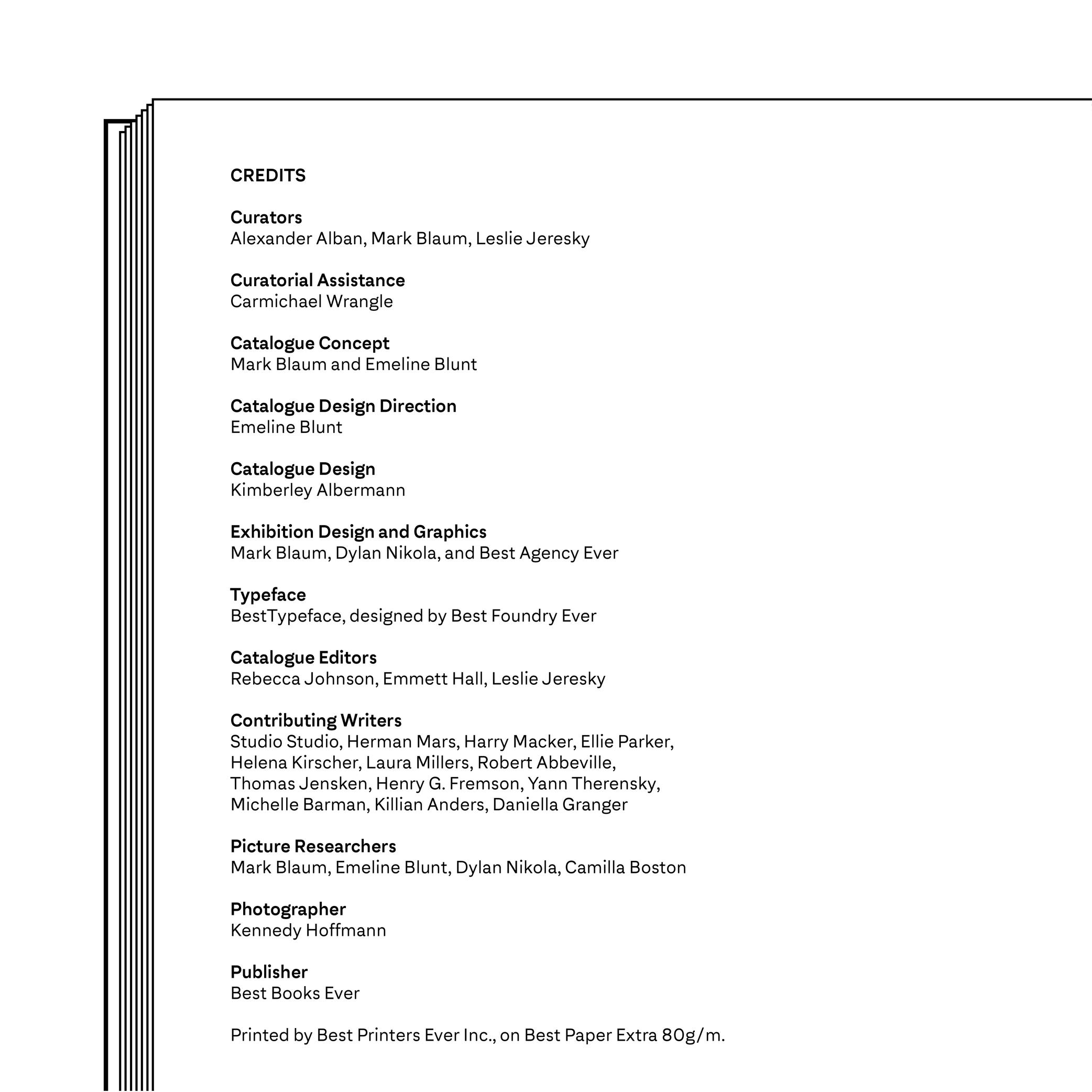
(Read More)版权页(或出版说明)是有关作品或项目制作的提示性信息列表。其范围包括参与人员的姓名和角色、所用字体、纸张的品牌和种类、生产商和生产地点,以及网站的域名等等。
贝齐耶曲线
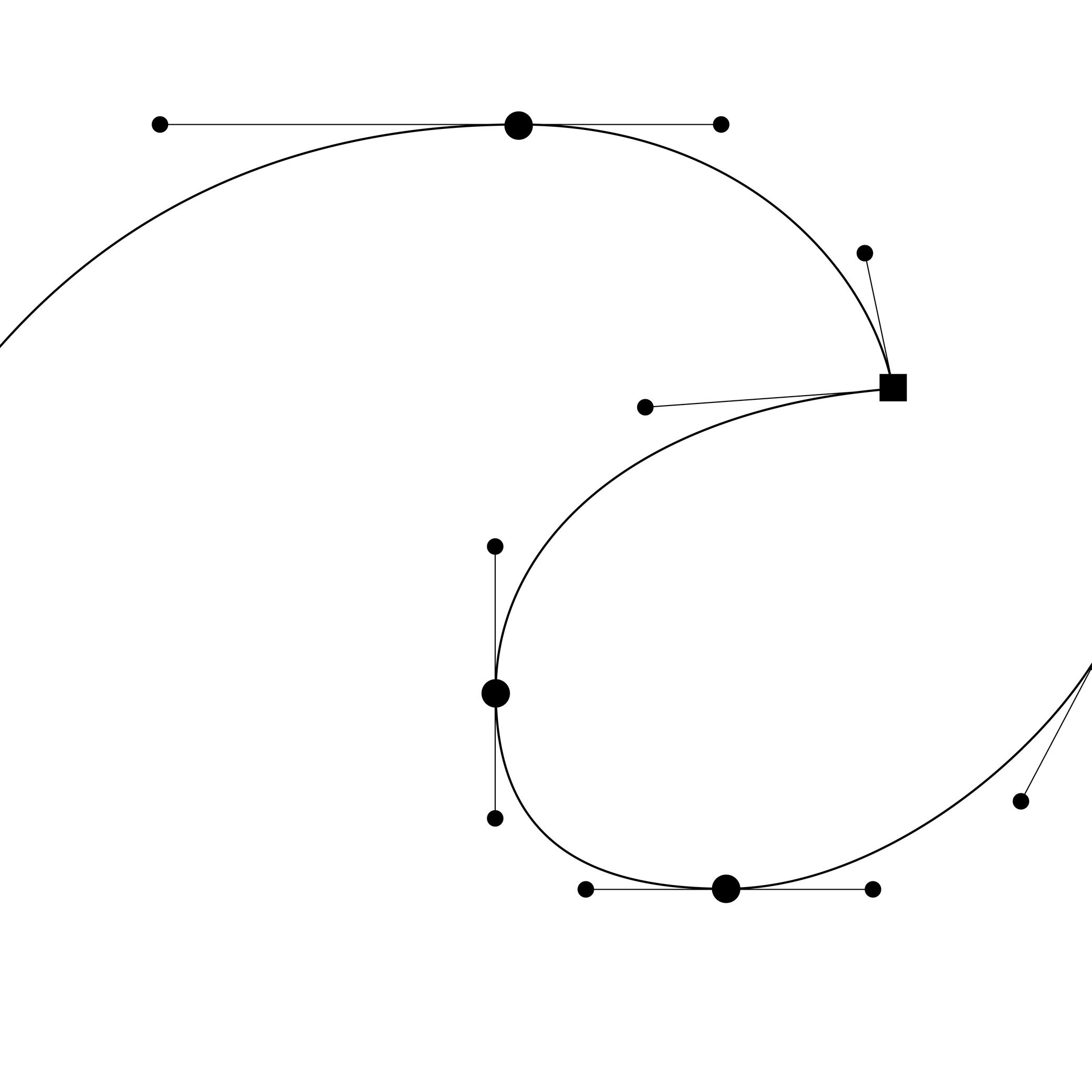
(Read More)在字体设计中,贝齐耶曲线是在数字化软件中放置节点和手柄来绘制的矢量轮廓。这种技术允许我们将数字形状记录并栅格化地再现出来,并保持曲线质量不发生太大变化。
历史
贝齐耶曲线是由法国数学和物理学家保尔·德·卡斯特奥(Paul de Casteljau)在1959年开发的。当时他正在为汽车品牌雪铁龙工作,他发明了一个数学方程式以改进汽车外壳的设计过程。法国工程师皮埃尔·贝齐耶(Pierre Bézier)在为雷诺汽车工作时使用了同样的技术,利用数字工具创造出了造型。直到 1985 年,雪铁龙解除了工业保密条款,德·卡斯特奥才得以谈论自己的工作,皮埃尔·贝齐耶也得以公开提及自己的工作。
1982年,贝齐耶曲线被美国计算机科学家约翰·沃诺克(John Warnock)用于为他与查尔斯·格斯克(Charles Geschke)共同创立的公司开发描述和定位数字造型和轮廓的技术:Adobe系统。
更多
贝齐耶曲线有两种类型:三次曲线和二次曲线。
一个三次贝齐耶曲线需要四个点的定位(两个点和两个手柄),在两两点之间形成了三段线条。Postscript字体格式使用三次曲线。
二次曲线由三个点(两个点和一个控制点)来创建一条曲线,中途有两个部分被切断,以确定曲线在哪里转到另一个点。TrueType字体格式使用二次曲线。
备选字符形
(Read More)由于多种原因,字符形可以有很多的变体。 最常见的有以下:
- 特定的语境(例如针对大写字母,原本为小写适配的标点符号可以替换成与大写字母对齐的字符形);
- 字符形的风格变体(例如花体字的备选);
- 本地化语言的偏好(本地化变体)。
在数字文件中,它们的名称都有与 Opentype 特性代码对应的标签(parenleft.case、A.swsh、Ldot.locl 等等),因此它们能轻松地在支持这些特性的应用程序中被处理。
边距
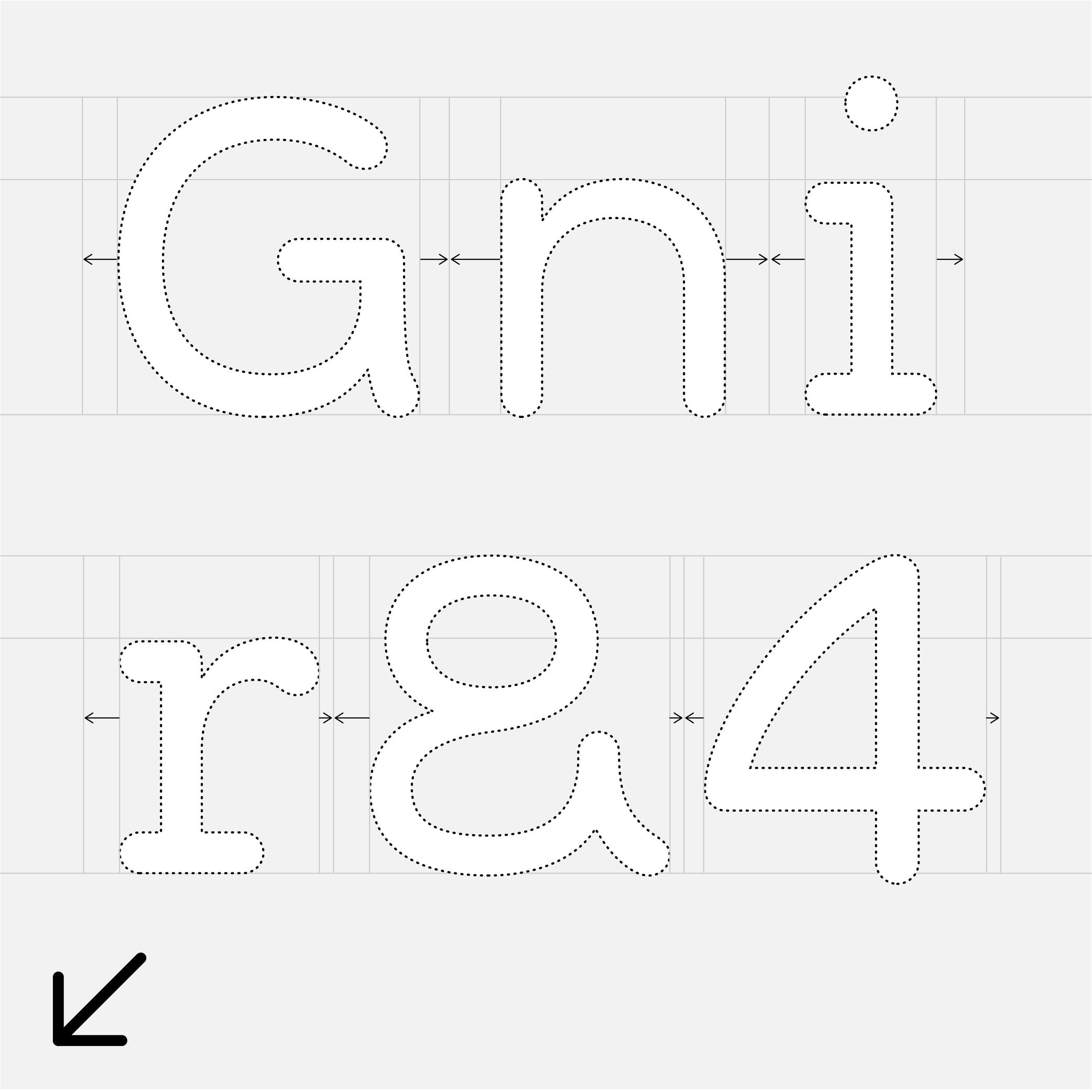
(Read More)边距是指字形的侧面与其边界框之间的距离。在水平书写的字体中,总是存在左边距 (LSB) 和右边距 (RSB)。管理边距值就是管理 “字体的字间距”。
变音符
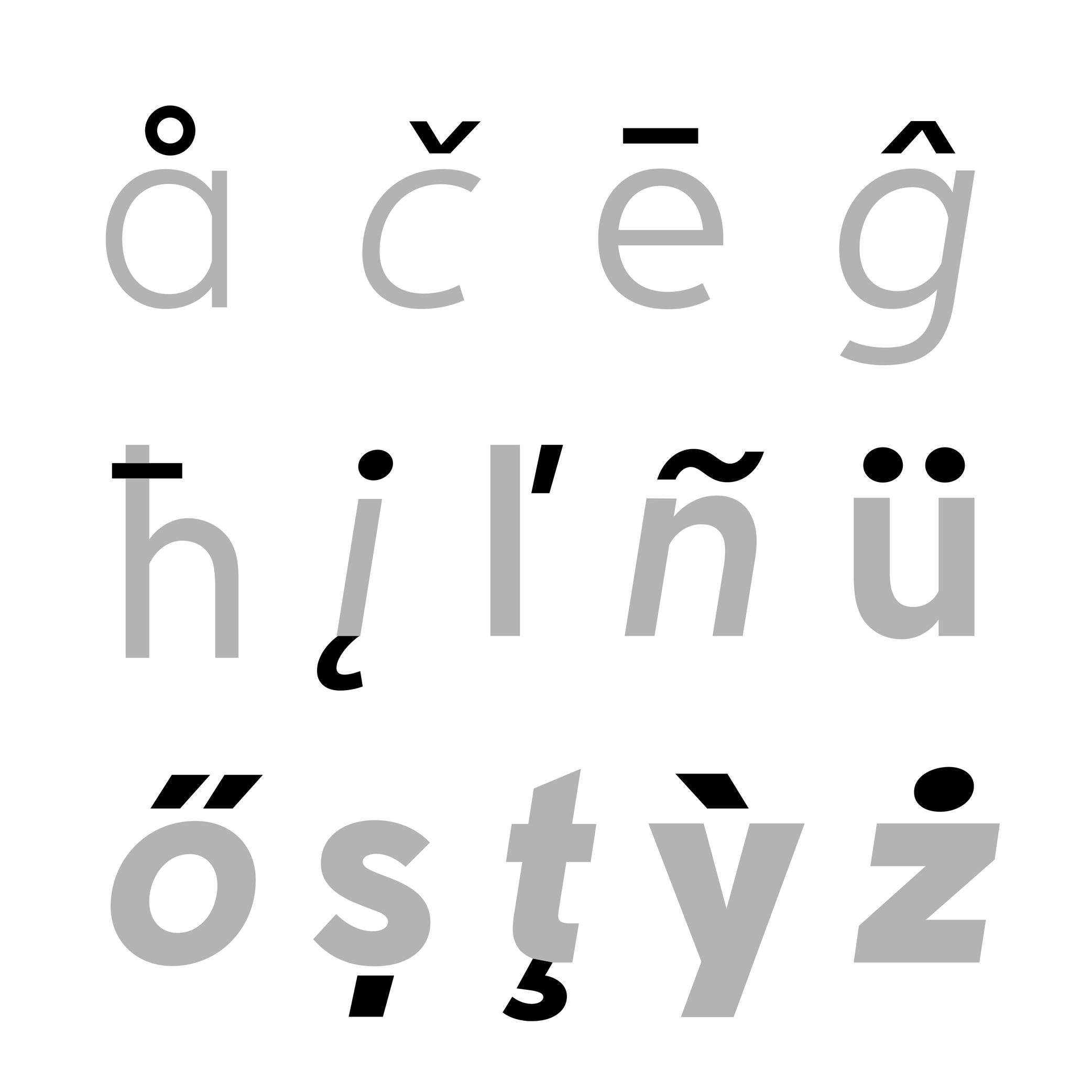
(Read More)变音符是加在字母上的标记。它们可以在字母的上方、下方或附着在字母上。在大多数使用变音符的语言和文字中,变音符会给字母带来不同于字母本身的声调。
拉丁字母表
拉丁字母用于许多语言。它们中的大多数都有使用变音符,为字母带来(有时是非常微妙的)声音变化。在不同的语言中,变音符的发音可能不同。例如,在法语、葡萄牙语和土耳其语中都使用字母ç,但是发音就很不一样。其他语言甚至将多个变音符与同一个字母组合在一起(如越南语中的 ở)。
阿拉伯字母
在阿拉伯字母中,字母的发音因其所附加的变音符号(或不附加变音符号)和使用的语言而不同。
汉语拼音
20 世纪 50 年代,中国大陆创建了一种新的拼音系统,以方便汉语学习: 拼音借用了拉丁字母和变音符作为声调标记。
设计
在创建字体时,各种变音符号都是单独设计的,然后在字体设计软件中作为部件与字母组合。它们需要:
- 在视觉上对齐到一致的高度(指的是放置在同一区域的变音符);
- 一致的粗细和灰度
- 对每种语言来说,变音符号与字母的相对位置要让人觉得很 “自然”。
部件
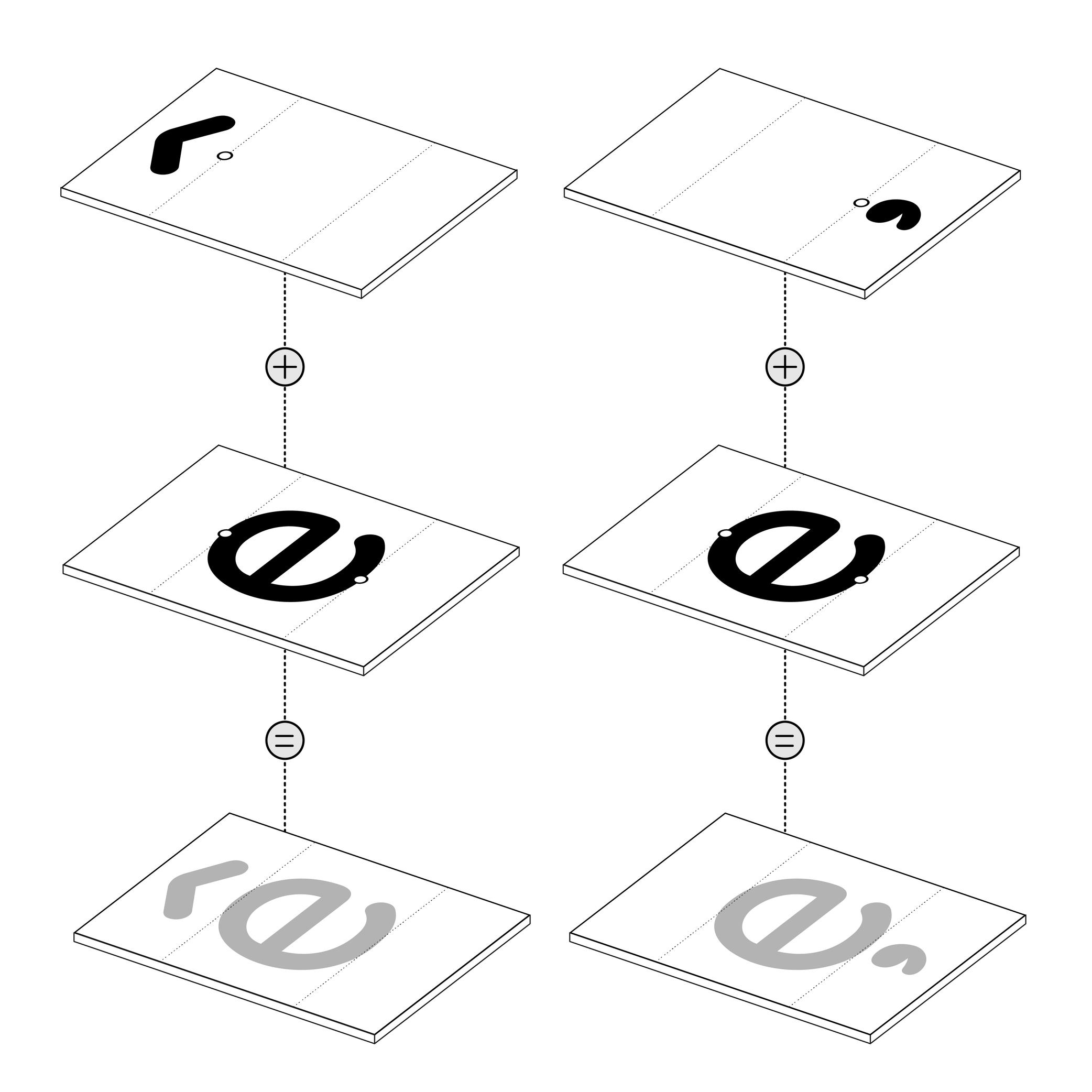
(Read More)数字字体文件中的许多造型在多个字符形中重复出现。这些都可以转化为部件。部件是作为单个字符形设计的部分(如变音符的 “尖角”),可以借用以形成其他字符形(如 é)。
使用组件而不是复制粘贴轮廓,这可以更好地控制一致性,并减小最终字体文件的大小。
超文本
(Read More)超文本链接是指数字文本的一部份链接到另一个页面或网站。
它通常以不同的颜色或样式加下划线或高亮显示。
插值
(Read More)可变字体技术允许用户在两种或多种特定样式(称为母版)之间进行调节出多种变化,同时保证高精度和小得多的字体文件。
当我们在母版之间调节时,我们看到的是插值。它们是根据两个(或多个)母板的数据以数字方式计算出的轮廓和形状。
重叠
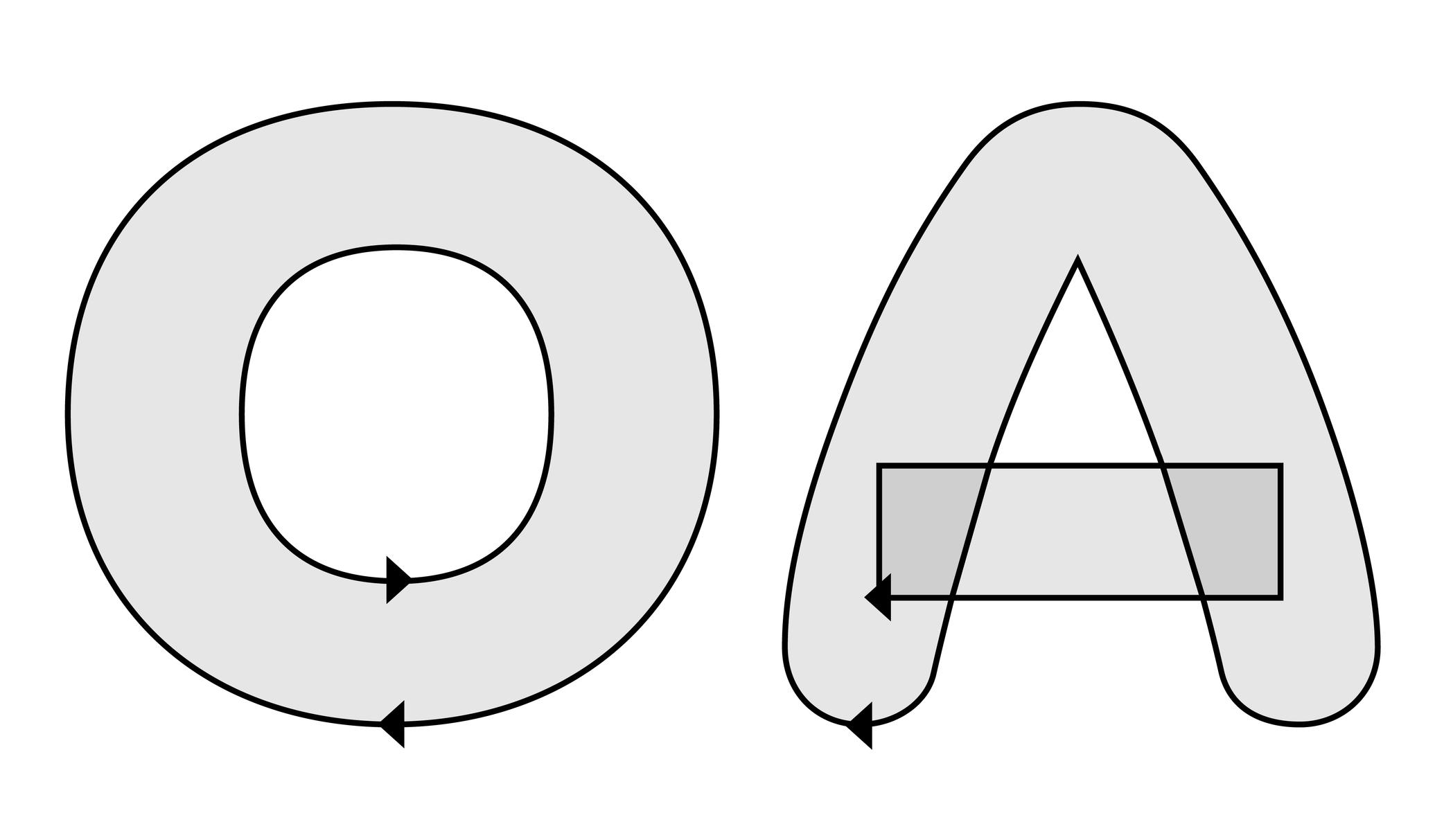
(Read More)在字体设计应用程序中设计字符时,可以将两个造型的轮廓重叠在一起,形成更复杂的形状(字母 E 可以分成几段),或者像字母 O 一样,形成一个字腔,轮廓较大,内部较小。
这两种效果可以通过改变轮廓的相对方向来控制。
单位
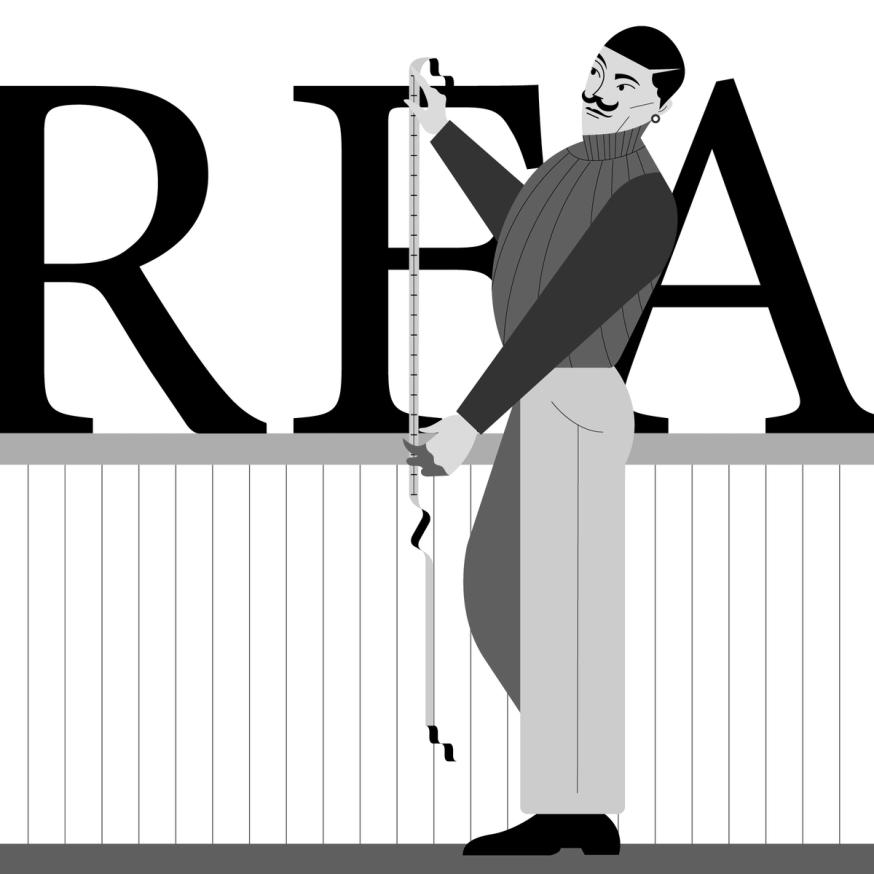
(Read More)测量字体大小使用一种特定的单位,称为 “点”。
多年来,全球各地使用了多种不同大小和名称的单位,从迪多、西塞罗和派卡点到英寸(这些仅用于拉丁字体)。
导出
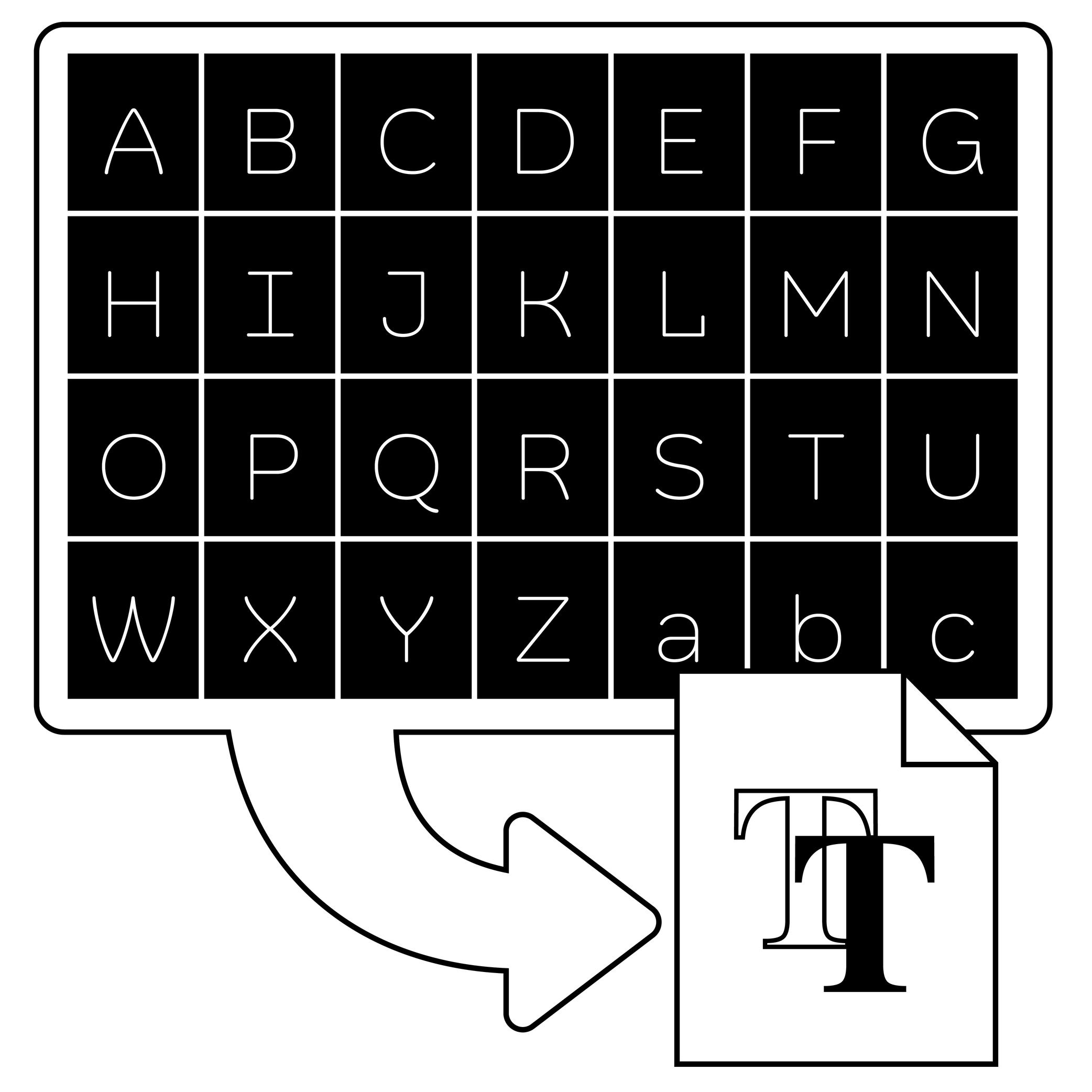
(Read More)在字体设计应用程序中,将设计文件(工作文件)转换为可以安装和使用的其他格式(字体文件)的操作称为 “导出”。
最常见的导出格式是用于印刷的 .otf(OpenType)、.ttf(TrueType)和用于网站的 .woff 或 .woff2(网页开放字体格式)。
大小写敏感
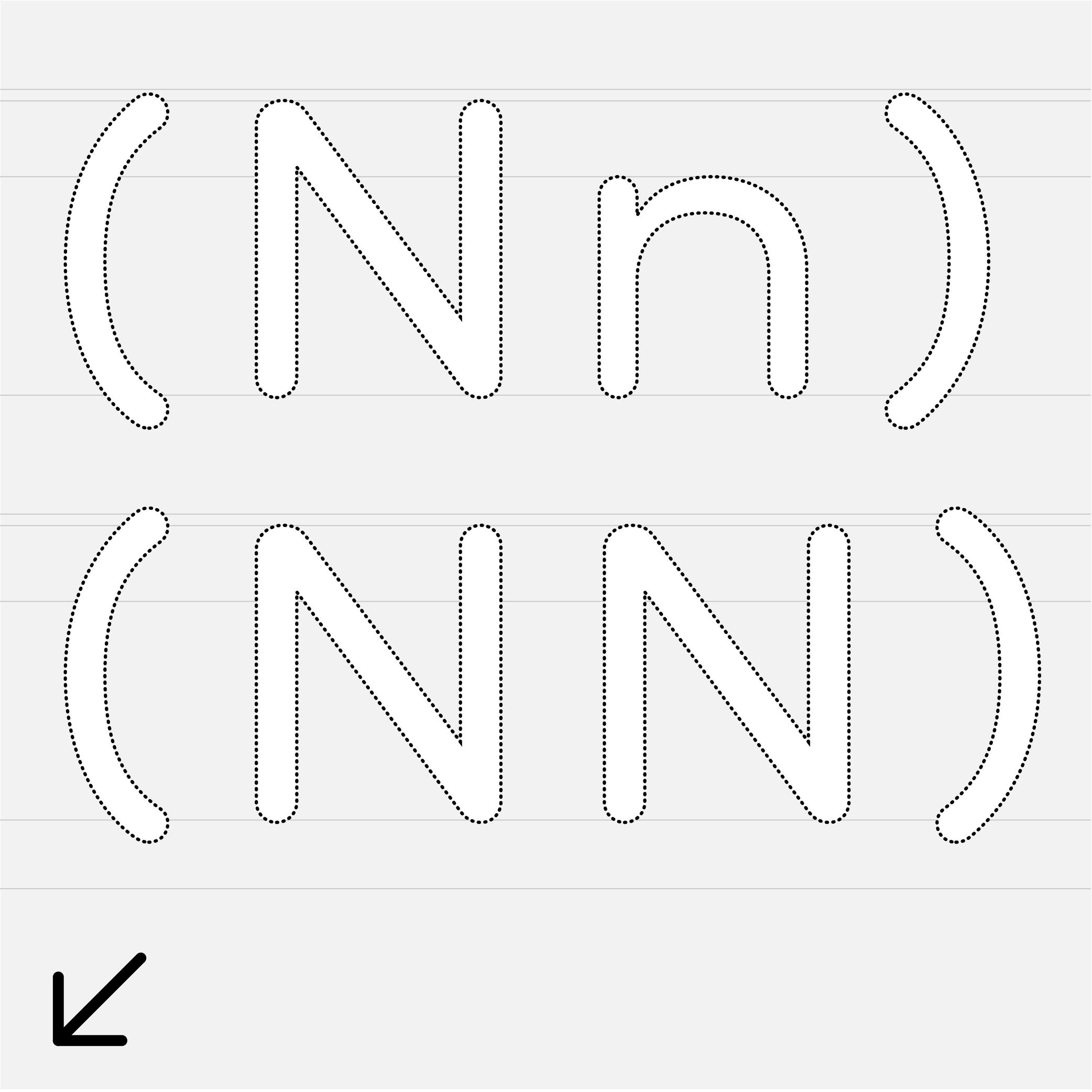
(Read More)默认情况下,大多数标点符号和一些字符的设计,是考虑与最常用的小写字母组合在一起使用的。
当与大写字母组合时,有些字符需要调整,以便在视觉上与大写字母对齐。好的字体需要这些变体,这样用户才能有足够的工具进行高质量的微观字体排印。这些变体被称为大小写敏感备选字,通常带有扩展后缀 “.case”,可在支持 OpenType 功能的应用程序中访问或激活。
大写字高
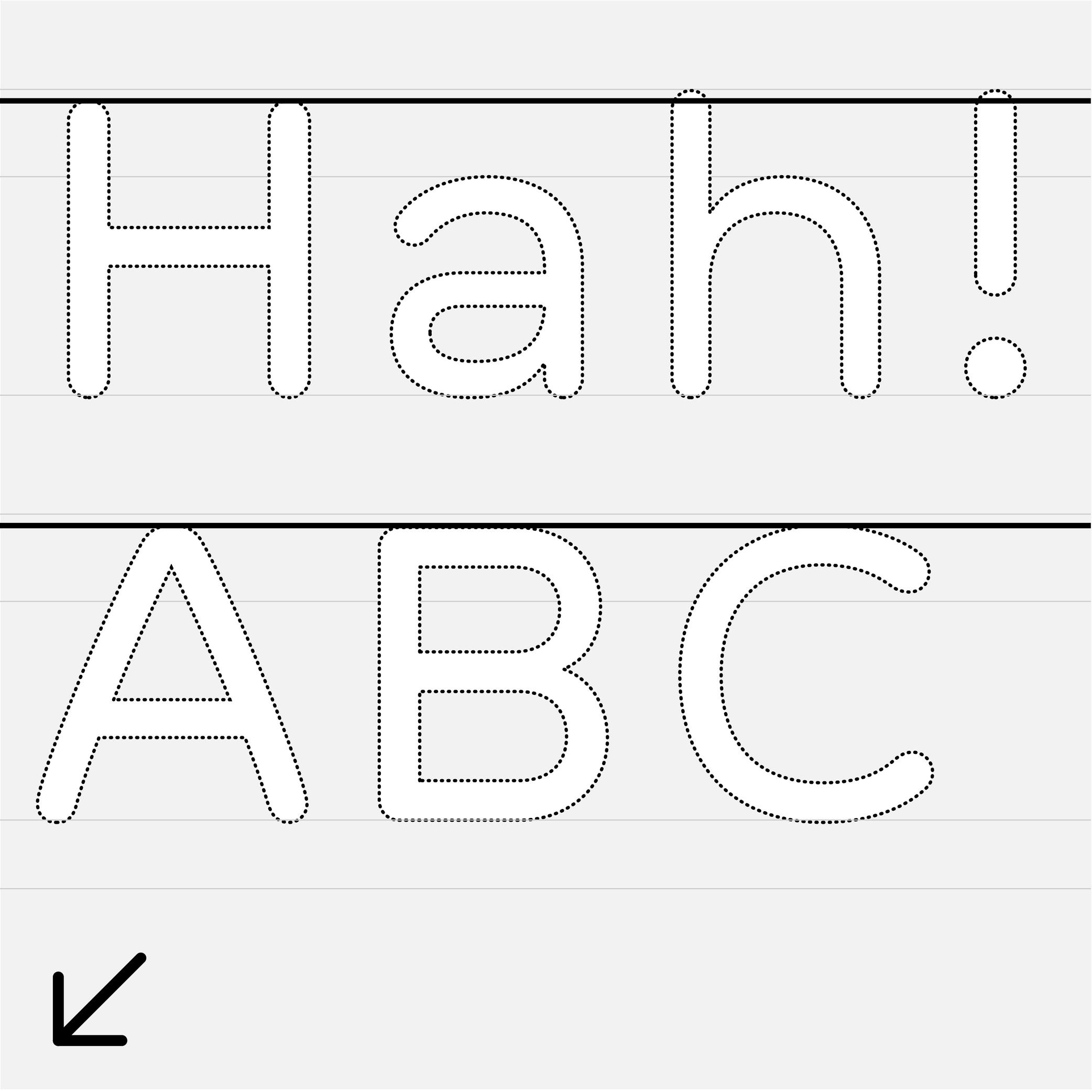
(Read More)大写字高位于方形大写字母(如 H)的顶端。 大写字高通常低于上伸部高度,是拉丁字体的主要参考线之一。
等宽字体
(Read More)在字体设计中,为了确保视觉平衡,字形的宽度和/或间距值会根据样式的重量而改变。然而,有些字体被设计为等宽(也称为多路复用),这意味着同一字形在该系列的所有字重和样式中都保持相同的宽度。
这一特点有利于数字排版,尤其是当用户或浏览者与数字屏幕上的文本之间存在交互时。例如,在悬停或点击时,文字或部分文字可以切换到不同的样式,而排版不会变化。
多种母版
赞助者:R-Typography 。字体:Montris 。设计师:Rui Abreu。2024年出版。
(Read More)可变字体技术允许用户在两个或多个特定样式(称为母版)之间进行指引或使用多种变化,具有高精度和更小的字体文件。
只要使用了两个以上的母版,就会产生一个更复杂的可变字体文件,这就是多母体字体(简称 MM)。
复刻
(Read More)复刻字体是一种(数字)字体,其设计源自现有字体(最常见的是印刷字体:金属、木质或照相排版)。
复刻字体的设计不可避免地包含了设计者的独特细节,从对最初设计的解释,到分析纸张上的印刷效果,再到不同分辨率下的屏幕效果。如今,我们可以看到从同一种字体复刻设计出的多种字体,但每种字体都有(有时是非常微妙的)差异。例如,我们可以想到 Garamond 字体的多个版本。
对于刚开始学习字体设计的学生来说,从连续文本字体中重新汲取灵感被认为是一项很好的作业,因为这可以让学生在进一步尝试更多创意之前,更熟悉“传统”的风格。
高度
插画作者:Jonny Wan 。
(Read More)对于一个字符集中的每一类字符形(大写、小写、小型大写等),设计者都会使用特定高度的参考线。它们有助于保持整个字体中每个字符形的造型和不同元素位置的一致性。
骨架
插画作者: Pauline Fourest (Spaghetype )。
(Read More)许多术语借用了建筑学或人体和动物解剖学的术语来指定和描述字母和其他字符的各个部分。我们甚至可以说是字体设计 ”解剖学”。
骨架是中心线,字形的每个部分(字重、笔画的粗细对比、弧度、末端等)都是围绕着它建立的。在一个字体系列的多种样式中保持骨架相同,顾名思义就是保持相同的结构,这也是保持设计一致性的主要方法之一。
合成字体
(Read More)在大多数文本处理工具中,都可以应用不同的样式(粗体、斜体、下划线或删除线)。
如果所选字体中没有这些样式,即使没有设计,系统也能 “自动” 生成类似的效果(不建议这样做,但在需要时会很方便)。
在这种情况下生成的字体称为合成字体。
弧笔
插画:Words of Type。
(Read More)字形的弧笔是指为了达到视觉上的平整度而略微超出其他字母高度的部分,例如圆形字母与方形字母相比。
详情请参阅 “视觉修正”。
字体替换
(Read More)只要文件中包含的文本使用的字体没有安装在用户的设备上,系统就会用另一种字体替换,作为备用解决方案。这就是字体替换。
字体/字型
(Read More)从金属活字时代开始,字体就是一套特定样式和字号的铅字。例如,10 点的 Times New Roman 常规体、16 点的 Times New Roman 粗体和 16 点的 Times New Roman 粗意大利体,是 Times New Roman 字体的三种不同的字体(样式)。
字体一词源于法文 “fondre”(意为 “熔化”),因为字符是通过熔化铅混合物,倒入铜模中成批生产出来的。
在数字世界中,字体现为一种特定样式字体的独立字库文件。另一个例子是 Helvetica Neue 细体和 Helvetica Neue 细斜体是两种独立的字库文件。
在中国大陆的国标文件中,将 font 翻译为 “字型”。在中国大陆的实际语用中,也常将 “字库” 指代 font 或 typeface,甚至是 foundry,如 “我是做字库的设计师”、“这是字库字体”、“某家字库”。在港台地区,“字型” 对应的是 typeface,而 “字体” 则是 font。